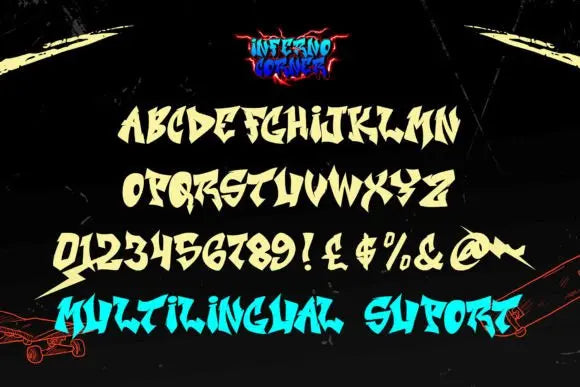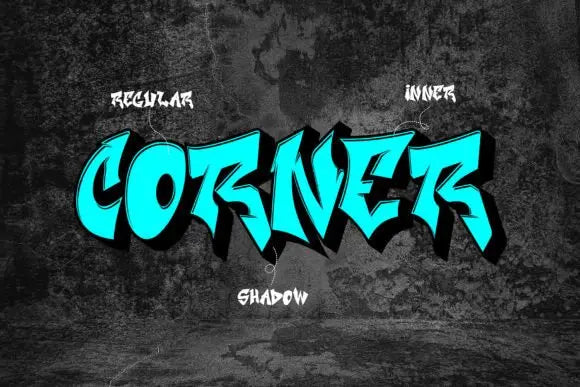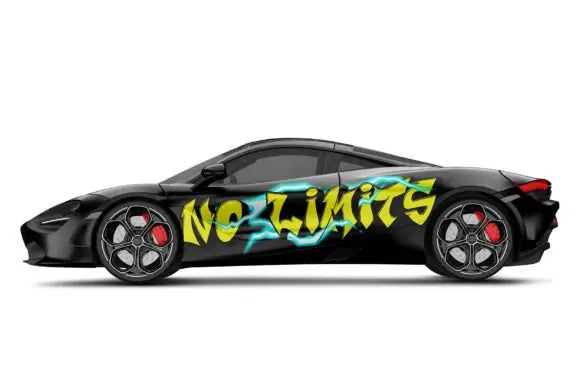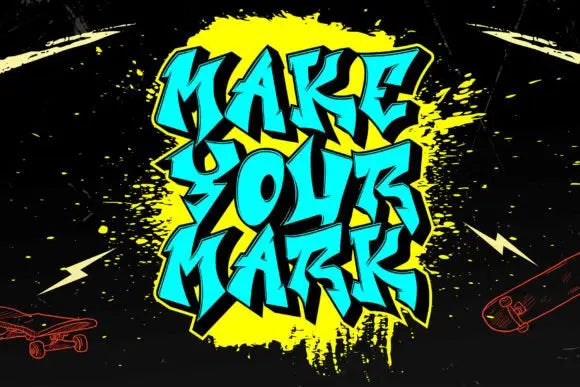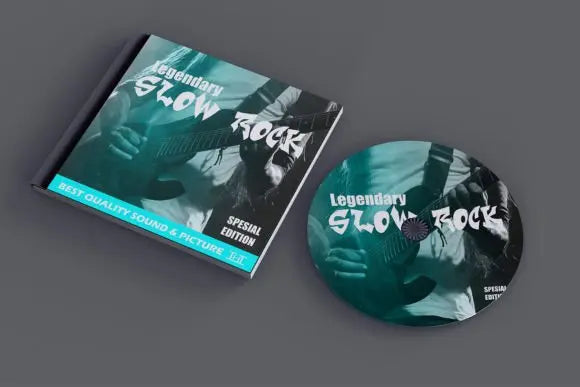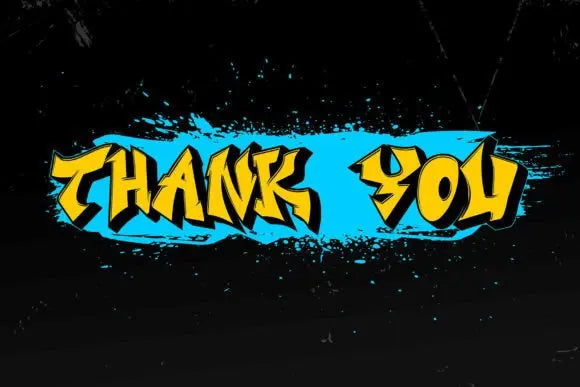
Fuente Inferno Corner
“Inferno Corner” es una fuente de graffiti en capas en 3D caracterizada por esquinas afiladas. Fuentes como esta incorporan múltiples capas para crear un efecto tridimensional y enfatizar los bordes angulares o puntiagudos, lo que a menudo mejora el dinamismo y el impacto visual de la fuente.
Esta fuente es particularmente adecuada para diversos proyectos relacionados con la calle donde se desea un estilo tipográfico atrevido y atrevido. Ya sea que se utilice en carteles, arte callejero o cualquier proyecto de diseño dirigido al entorno urbano, “Inferno Corner” puede brindar un aspecto llamativo y que llame la atención a su texto, contribuyendo a la estética general de estilo callejero de su proyecto.